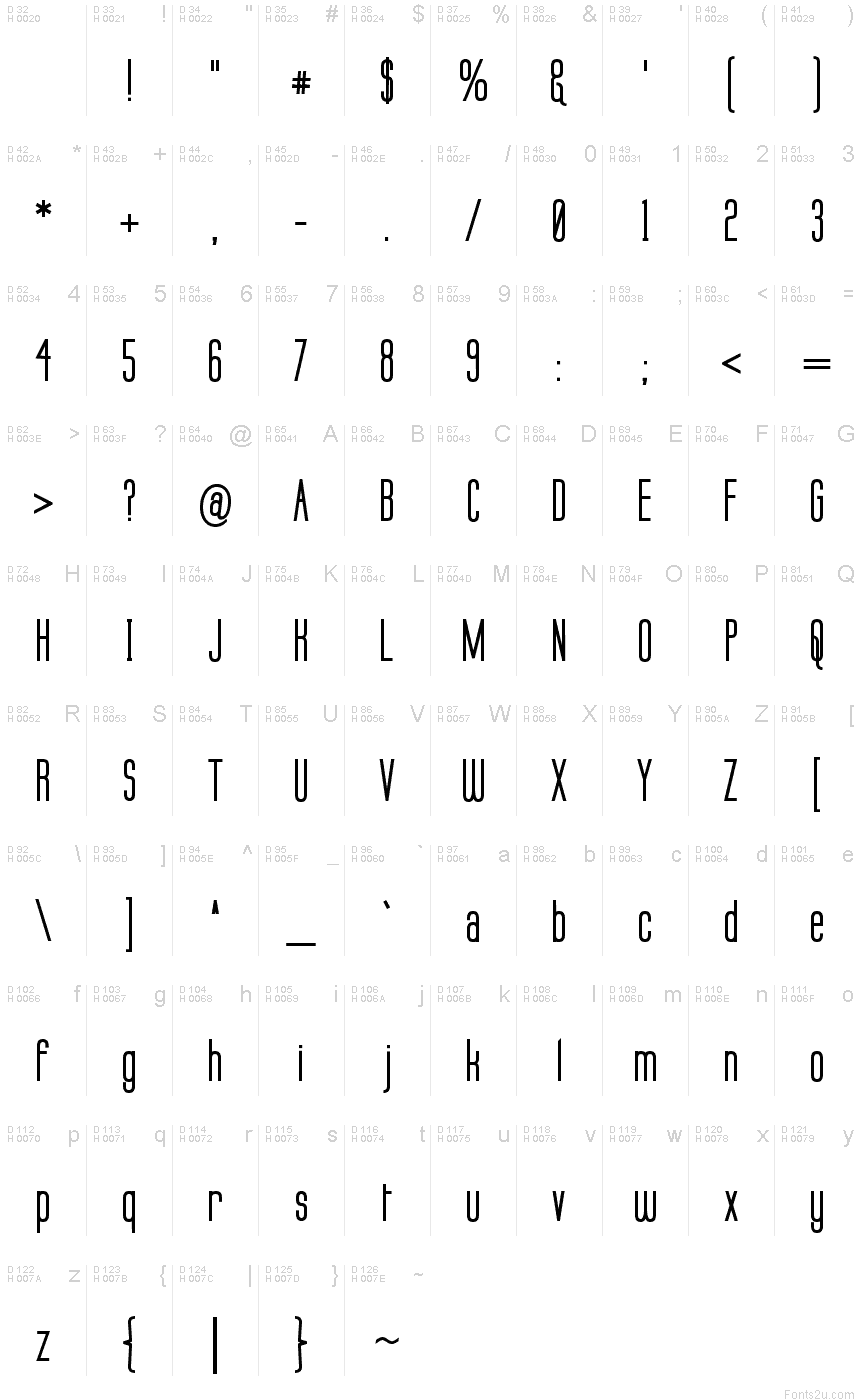
Labtop Bold, autorstwa Grahama Meade'a i Apostrophic Labs, to darmowy krój displayowy w stylu retro o smukłej, łagodnie geometrycznej estetyce. Litery sprawiają wrażenie wysokich i wąsko osadzonych, łącząc proste linie pionowe z zaokrągleniami, dzięki czemu alfabet plasuje się gdzieś pomiędzy kompaktowym oznakowaniem a brandingiem z wczesnej ery komputerowej, unikając przy tym efektu sztuczności.
Doskonale sprawdzi się na plakatach, okładkach płyt, w identyfikacjach wizualnych związanych z technologią, na planszach tytułowych, opakowaniach czy w krótkich nagłówkach magazynowych – wszędzie tam, gdzie darmowy font musi wypełnić wąską przestrzeń, dodając odrobinę klimatu vintage. Wykorzystaj go, gdy chcesz, aby krótkie słowa, inicjały lub monogramy wyglądały czysto, ale z nutą nostalgii; napięty rytm i zaokrąglone kształty nadają nawet prostym napisom wyrazistego charakteru.
Labtop Bold